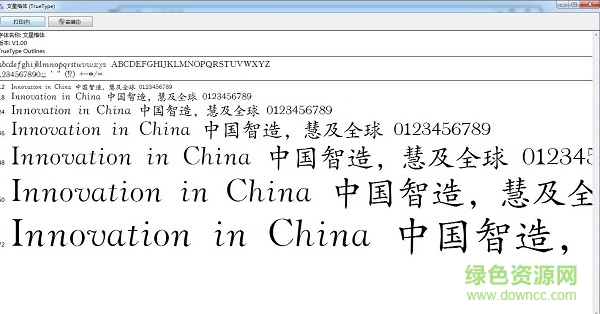
文星楷體字體是一款免費的楷書字體,該字體結(jié)構(gòu)規(guī)范,筆畫平直,點畫清楚,適用于于書籍排版、ppt正文、影視等各個領(lǐng)域,歡迎大家在綠色資源網(wǎng)下載!
【大楷】
一般情況下,人們把一寸以上、數(shù)寸以下見方的真書稱為大楷。較此更大的真書大字被稱為“榜書”、“擘窠書”。掌握好大楷的點畫、結(jié)構(gòu)、布白,做到點畫準確精到,結(jié)構(gòu)疏密得當。
【小楷】
小楷,顧名思義,是楷書之小者,創(chuàng)始于三國魏時的鐘繇。他原是位隸書最杰出的權(quán)威大家,所作楷書的筆意,亦脫胎于漢隸,筆勢恍如飛鴻戲海,極生動之致。